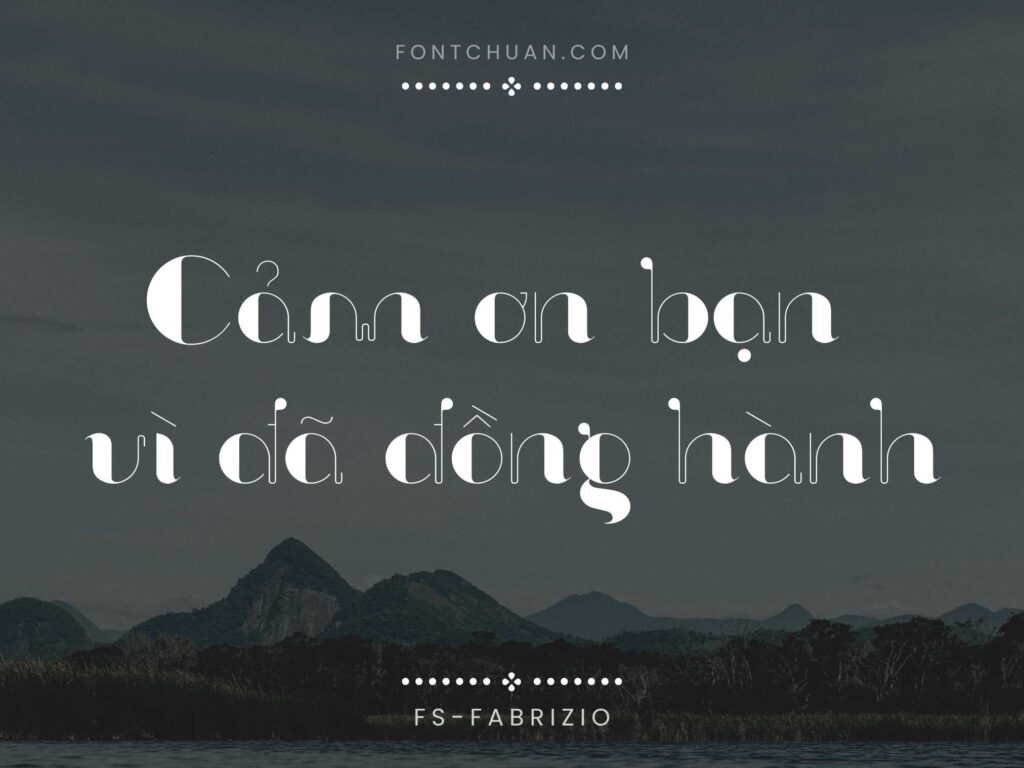
Font FS Fabrizio Việt Hóa
Tác giả Font: Federico Landini
Fabrizio là một kiểu chữ hiển thị hiện đại, được thiết kế bởi Ari Rafaeli. Font này nổi bật với sự tương phản cao giữa các ký tự viết hoa theo phong cách Didone và các ký tự viết thường độc đáo, tạo nên sự kết hợp thú vị giữa cổ điển và hiện đại. Nhờ sự Việt hóa của Phông Chữ Việt, Fabrizio hỗ trợ đầy đủ các ký tự tiếng Việt, giúp người dùng dễ dàng áp dụng trong các thiết kế đa ngôn ngữ. Thành viên của Font Chuẩn đã sưu tầm và chia sẻ font này nhằm đáp ứng nhu cầu của cộng đồng thiết kế.
Về đặc điểm thiết kế, Fabrizio sở hữu các đường nét sắc sảo, thanh mảnh và tinh tế, mang lại cảm giác sang trọng và lịch lãm. Font bao gồm đầy đủ chữ hoa, chữ thường, số và các ký tự đặc biệt, hỗ trợ đa ngôn ngữ. Fabrizio đặc biệt phù hợp cho các dự án thiết kế như bìa sách, poster, bao bì sản phẩm và các ấn phẩm quảng cáo, nơi cần sự nổi bật và ấn tượng mạnh mẽ. Ngoài ra, font này cũng thích hợp cho các sự kiện như lễ hội, sinh nhật, Valentine và Trung thu, mang lại cảm giác ấm áp và gần gũi. Trong lĩnh vực ngành nghề, Fabrizio được ứng dụng rộng rãi trong quảng cáo, thiết kế thiệp cưới, giáo dục và công nghệ, góp phần tạo nên sự độc đáo và thu hút cho các sản phẩm và thương hiệu.